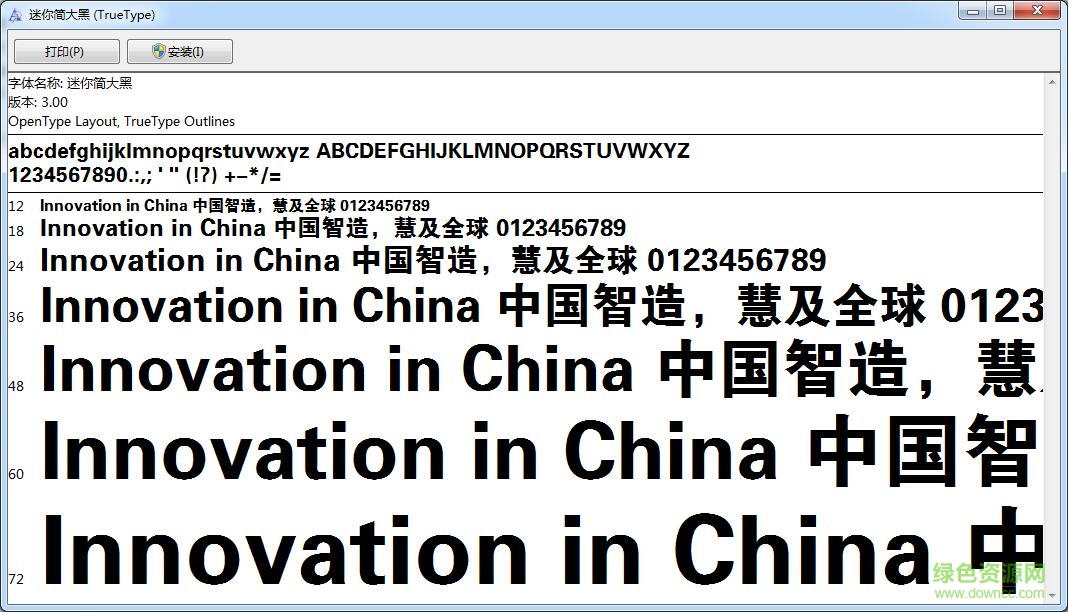
jdahei是什么字體?jdahei為迷你簡大黑,這款字體粗黑嚴謹、渾厚穩(wěn)重,非常具有現(xiàn)代感,綠色資源網(wǎng)還有方正大黑字體、漢儀大黑字體、文鼎大黑字體等海量黑體字體供你下載,想要的朋友們可千萬別錯過了這款經(jīng)典之作哦。
一般用于印刷、書面報告等比較正式的場合,多用于標題或標識重點,標題、燈箱廣告、標牌等領域也可適用!
相對于宋體而言,黑體字的橫豎筆畫的粗細要相對更直,“人工設計”的效果也更強,常被用于作為“力量較強的效果”和“時尚的效果”的處理 標題如果選用黑體來處理,會比宋體更容易給人帶來較為強烈的印象,因此黑體字的直觀效果相對于宋體等手寫體來說要更強一些。